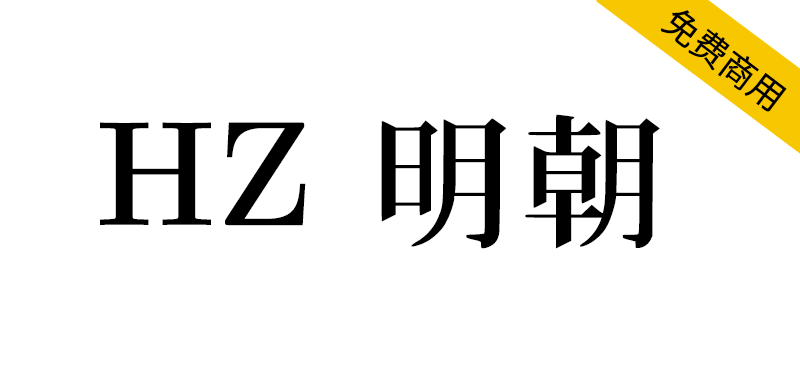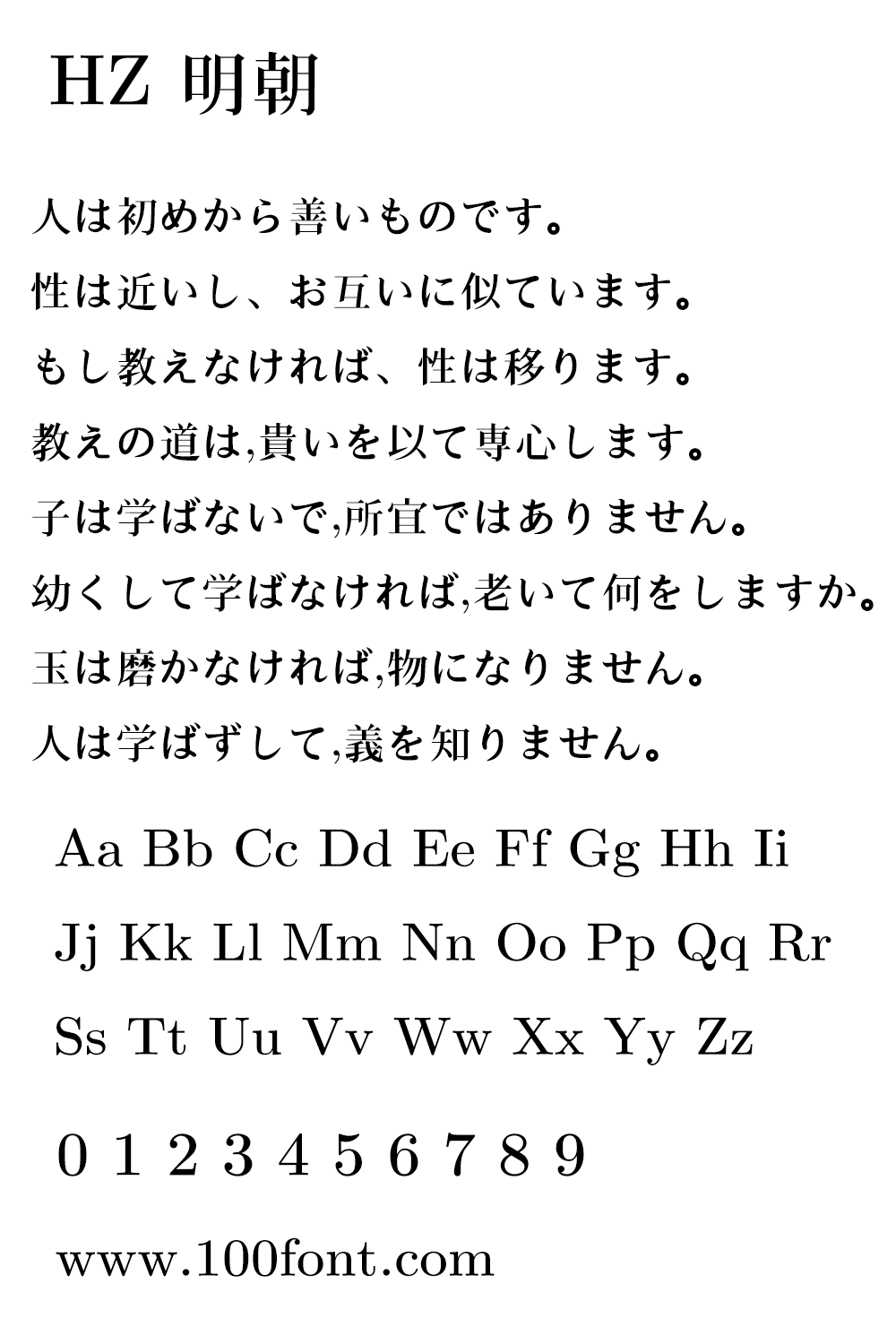
这是一个免费的OpenType cid的日文字体,来自字形维基(GlyphWiki)的CJK数据,有5个字重。
拉丁文、希腊文和西里尔字母并非源自字形维基(GlyphWiki),而是源自Computer Modern Unicode,因为GlyphWiki的Kage引擎是为中文字符设计的。
一些符号来自M+字体和GL Antique字体。
This is a free/libre OpenType CID-keyed Japanese font derived fromGlyphWiki's CJK data, with weight variations.
Latin, Greek and Cyrillic glyphs are not derived from GlyphWiki but fromComputer Modern Unicodebecause GlyphWiki'sKage engineis intended for Chinese characters and not good at LGC.
Some symbols are fromM+fonts andGL Antiquefont.